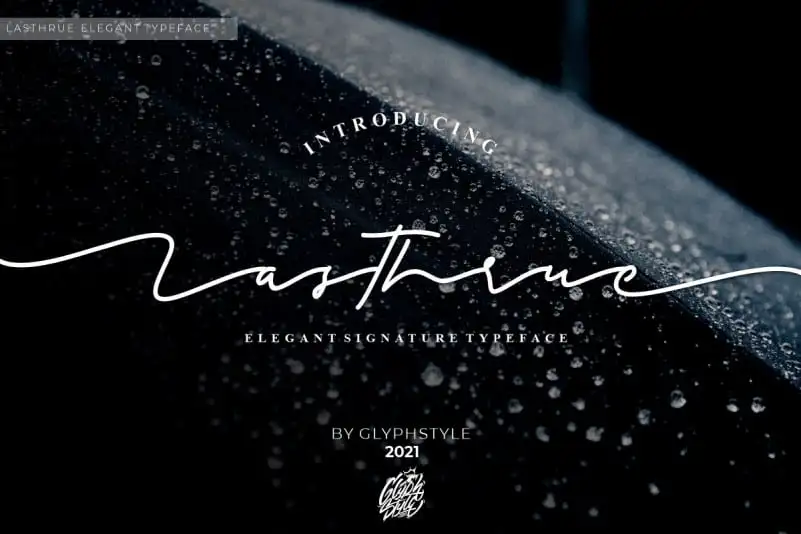
Lasthrue Signature Script Font – Download Grátis
A Lasthrue Signature Script Font é uma elegante escolha para quem busca um estilo de escrita que combine a sofisticação com uma naturalidade única. Esta fonte monoline apresenta curvas suaves e líneas finas, criando um equilíbrio perfeito entre seriedade e charme. Confeccionada para eventos como casamentos, logotipos empresariais, cards de negócios, marcas em água e logos de produtos, a Lasthrue Signature Script é uma fonte que transmite elegância e profissionalismo. Seja em um projeto de marca ou apenas em um documento pessoal, esta fonte proporcionará uma escrita única e memorável. Seu caráter natural permite que ela se destaque em qualquer ambiente, seja em formatos digitais ou impressos. Essa é a fonte perfeita para aqueles que desejam transmitir um toque autêntico e sofisticado através de seus projetos gráficos.